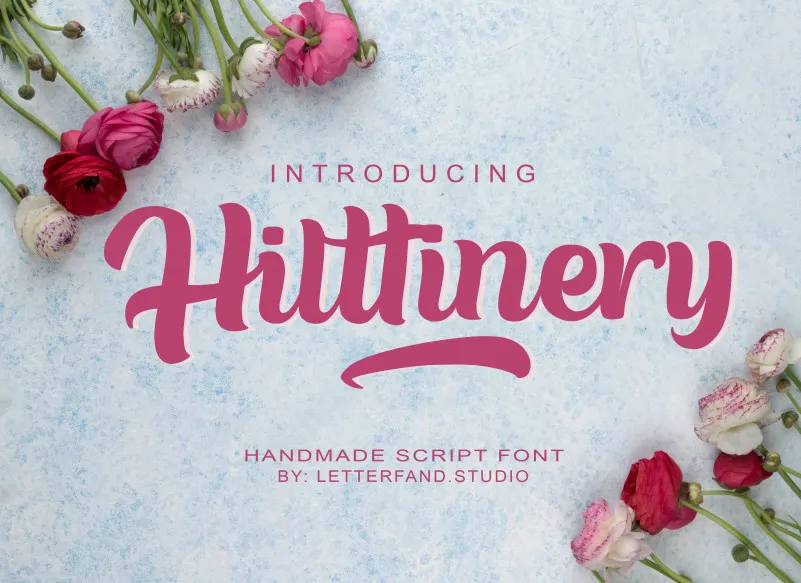
Hilttinery Script Font – Download Grátis
A Hilttinery Script Font é uma elegante escolha para designers que procuram um estilo handwritten moderno. Feito para aqueles que valorizam a naturalidade e sofisticação, essa fonte se destaca por seu aspecto luxuoso, tornando seus projetos ainda mais atraentes e adequados ao padrão atual dos designs. Se você busca uma opção única para dar um toque de personalização em suas criações gráficas, Hilttinery Script Font é uma excelente escolha. Combinada com qualquer design, ela cria um arluxo que certamente chamará atenção e fará sua obra sobressair da multidão. Não importa o tipo de projeto – seja logotipos, letras grandes ou infográficos, essa fonte oferece a combinação perfeita entre modernidade e elegância, tornando-a um recurso indispensável no seu arsenal criativo.
Designer: letterfand.studio